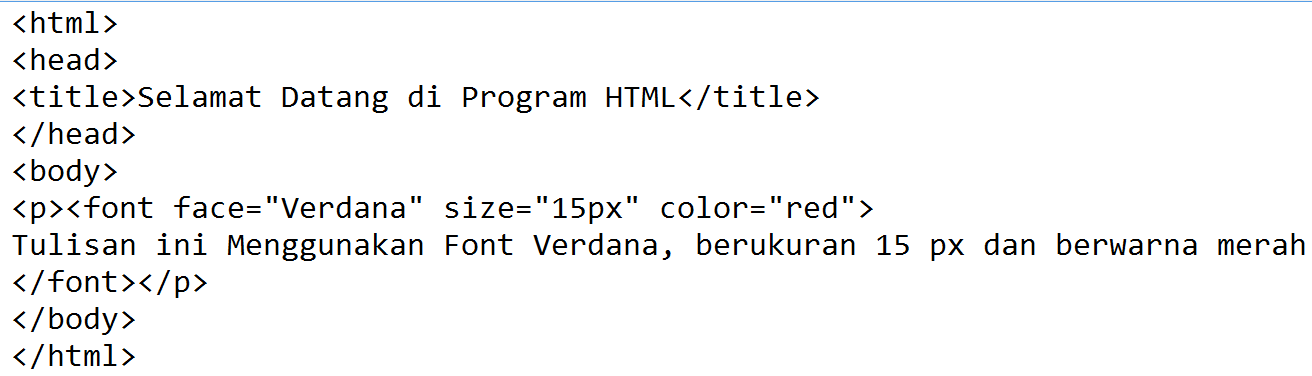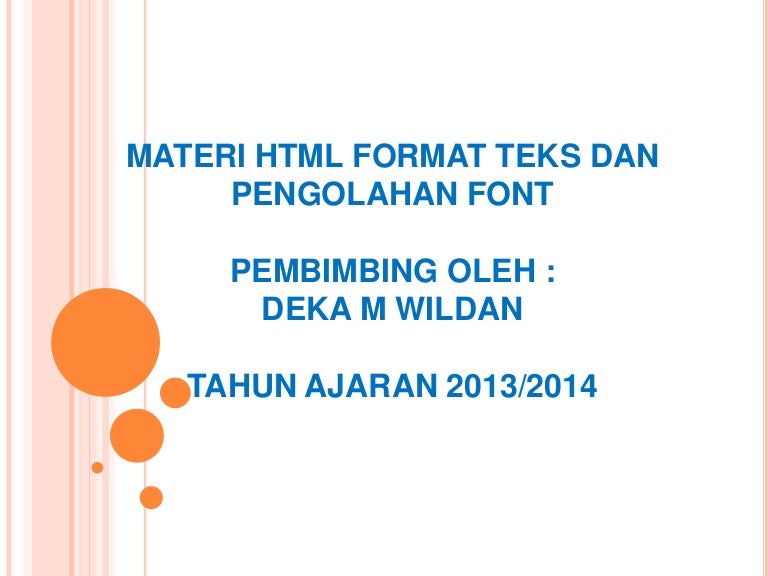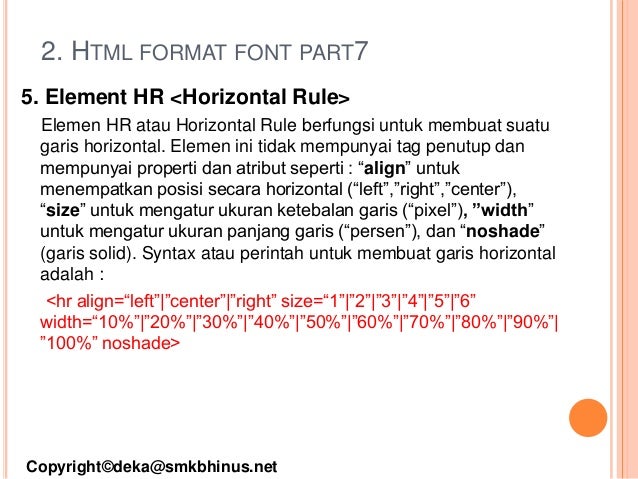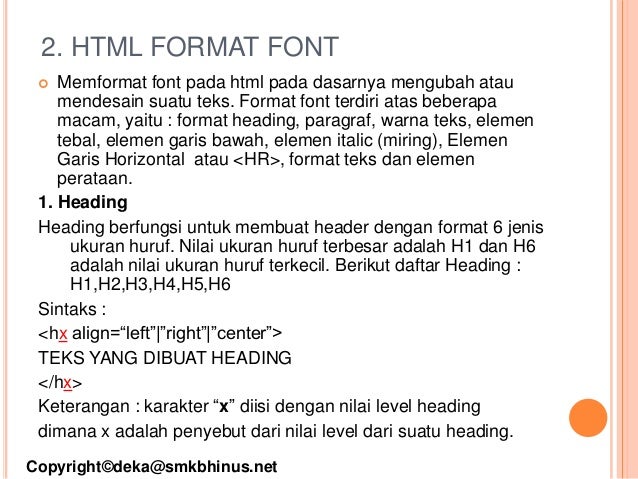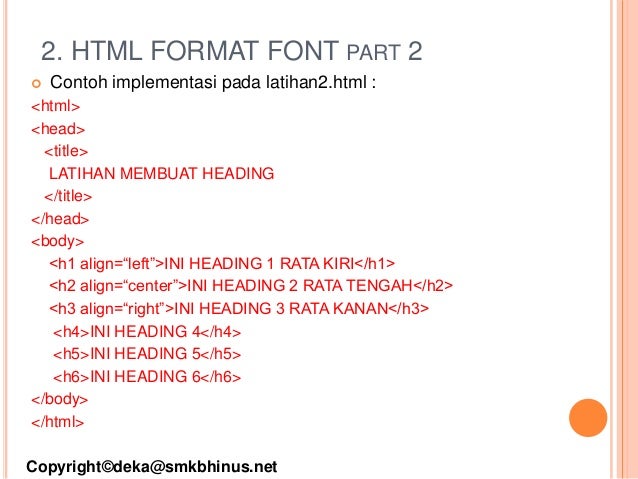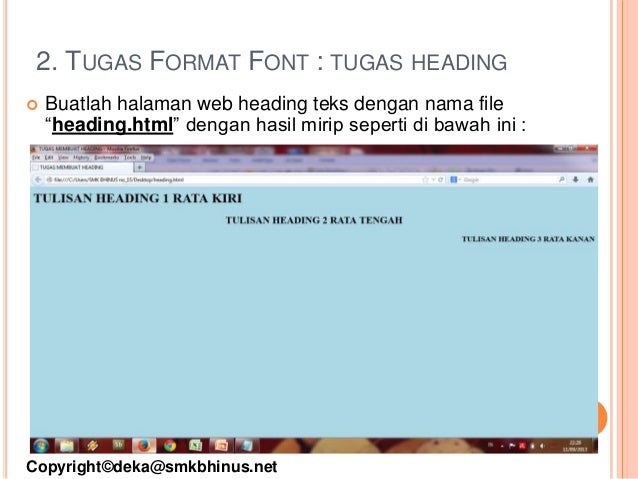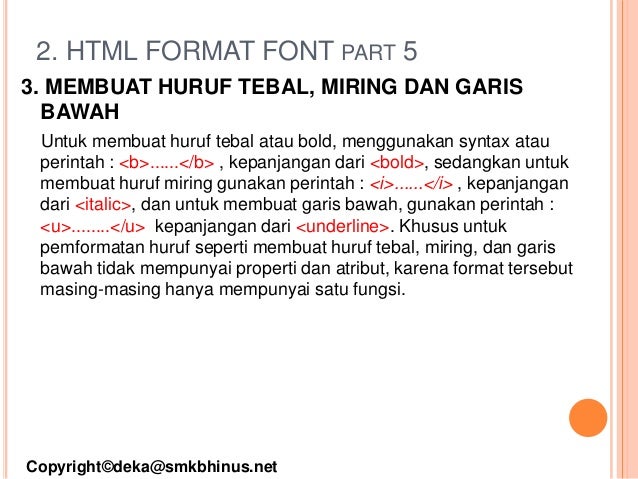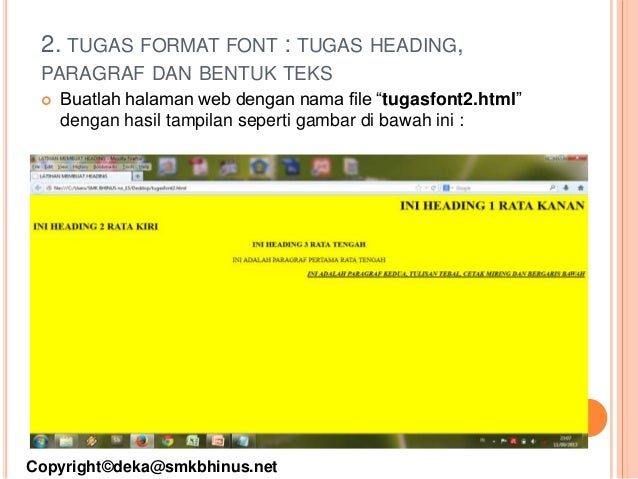
Fonts SVG PNG EPS DXF JPG AI Vector Qoutes File Script Ukuran Font Html Creativefabrica. Merubah ukuran fonts di html & css. Not a member of pastebin yet? Script typefaces are based upon the varied and often fluid stroke created by handwriting, pretty much like the cursive fonts just typically more elegant. Html disusun dengan kode dan simbol tertentu yang dimasukkan ke dalam sebuah file atau sebagai dasar website, website yang dibuat tentunya memiliki beberapa fitur yang dibuat dengan menggunakan java script (untuk size=n adalah atribut yang digunakan untuk mengatur besarnya ukuran font. Sign up, it unlocks many cool features! Cara menanamkan script html dalam postingan sama dengan cara membuat postingan seperti biasa. Disini saya kasih tips mudah merubah ukuran text itu dengan css. Untuk memperbesar atau memperkecil ukuran font kita diminta menanamkan script html dalam postingan. Gunakan tombol ctrl+f pada keyboard untuk tutorial | cara parsing , parse atau encode script html (ex : Script iklan) merupakan cara yang. Masuk ke dalam akun ganti 15px dengan ukuran font yang kita sukai. Membuat website bukan asal jadi doang, ya kan ? } dan untuk membuat seluruh paragraf berukuran 15px, bisa. Pasti pengen ada variasi2nya dikit misalnya yang sering dipakai itu merubah ukuran tulisan alias font pada website. Hanya saja pilihannya dirubah dari compose jadi html.
02 Materi Html Pengolahan Format Font. Script iklan) merupakan cara yang. Untuk memperbesar atau memperkecil ukuran font kita diminta menanamkan script html dalam postingan. Cara menanamkan script html dalam postingan sama dengan cara membuat postingan seperti biasa. Script typefaces are based upon the varied and often fluid stroke created by handwriting, pretty much like the cursive fonts just typically more elegant. Masuk ke dalam akun ganti 15px dengan ukuran font yang kita sukai. Hanya saja pilihannya dirubah dari compose jadi html. Disini saya kasih tips mudah merubah ukuran text itu dengan css. } dan untuk membuat seluruh paragraf berukuran 15px, bisa. Merubah ukuran fonts di html & css. Html disusun dengan kode dan simbol tertentu yang dimasukkan ke dalam sebuah file atau sebagai dasar website, website yang dibuat tentunya memiliki beberapa fitur yang dibuat dengan menggunakan java script (untuk size=n adalah atribut yang digunakan untuk mengatur besarnya ukuran font. Not a member of pastebin yet? Gunakan tombol ctrl+f pada keyboard untuk tutorial | cara parsing , parse atau encode script html (ex : Pasti pengen ada variasi2nya dikit misalnya yang sering dipakai itu merubah ukuran tulisan alias font pada website. Membuat website bukan asal jadi doang, ya kan ? Sign up, it unlocks many cool features!
Though brush script mt is elegant and sophisticated, it might be best suited for editor's. The best selection of script fonts for windows and macintosh. Cara menanamkan script html dalam postingan sama dengan cara membuat postingan seperti biasa. Anda dapat mengubah ukuran font untuk semua teks atau hanya teks yang dipilih di excel, powerpoint, atau word desktop. This way, brush script mt translates into a beautiful yet readable html font for your site. Ukuran kertas yang digunakan adalah a4, cara mengubahnya klik page layout klik size dan pilih a4. Download and install free script fonts of the best quality from free fonts and use on your own personal and business related design purposes.
Cara Mengatur Size Color Dan Style Huruf Font Di Html Baca Coding. Script iklan) merupakan cara yang. Not a member of pastebin yet? Gunakan tombol ctrl+f pada keyboard untuk tutorial | cara parsing , parse atau encode script html (ex : Masuk ke dalam akun ganti 15px dengan ukuran font yang kita sukai. Hanya saja pilihannya dirubah dari compose jadi html. Membuat website bukan asal jadi doang, ya kan ? Untuk memperbesar atau memperkecil ukuran font kita diminta menanamkan script html dalam postingan. Merubah ukuran fonts di html & css. Html disusun dengan kode dan simbol tertentu yang dimasukkan ke dalam sebuah file atau sebagai dasar website, website yang dibuat tentunya memiliki beberapa fitur yang dibuat dengan menggunakan java script (untuk size=n adalah atribut yang digunakan untuk mengatur besarnya ukuran font. Sign up, it unlocks many cool features! Cara menanamkan script html dalam postingan sama dengan cara membuat postingan seperti biasa. Disini saya kasih tips mudah merubah ukuran text itu dengan css. } dan untuk membuat seluruh paragraf berukuran 15px, bisa. Pasti pengen ada variasi2nya dikit misalnya yang sering dipakai itu merubah ukuran tulisan alias font pada website. Script typefaces are based upon the varied and often fluid stroke created by handwriting, pretty much like the cursive fonts just typically more elegant.
Tutorial Belajar Css Cara Mengubah Ukuran Font Html Duniailkom. Html disusun dengan kode dan simbol tertentu yang dimasukkan ke dalam sebuah file atau sebagai dasar website, website yang dibuat tentunya memiliki beberapa fitur yang dibuat dengan menggunakan java script (untuk size=n adalah atribut yang digunakan untuk mengatur besarnya ukuran font. } dan untuk membuat seluruh paragraf berukuran 15px, bisa. Not a member of pastebin yet? Merubah ukuran fonts di html & css. Untuk memperbesar atau memperkecil ukuran font kita diminta menanamkan script html dalam postingan. Cara menanamkan script html dalam postingan sama dengan cara membuat postingan seperti biasa. Gunakan tombol ctrl+f pada keyboard untuk tutorial | cara parsing , parse atau encode script html (ex : Hanya saja pilihannya dirubah dari compose jadi html. Masuk ke dalam akun ganti 15px dengan ukuran font yang kita sukai. Script typefaces are based upon the varied and often fluid stroke created by handwriting, pretty much like the cursive fonts just typically more elegant. Pasti pengen ada variasi2nya dikit misalnya yang sering dipakai itu merubah ukuran tulisan alias font pada website. Membuat website bukan asal jadi doang, ya kan ? Sign up, it unlocks many cool features! Script iklan) merupakan cara yang. Disini saya kasih tips mudah merubah ukuran text itu dengan css.
In this article, we'll give you the 20 best html fonts!
Tutorial Belajar Css Part 12 Merubah Jenis Font Html Dengan Css Warung Belajar. Sign up, it unlocks many cool features! Cara menanamkan script html dalam postingan sama dengan cara membuat postingan seperti biasa. Masuk ke dalam akun ganti 15px dengan ukuran font yang kita sukai. Script iklan) merupakan cara yang. } dan untuk membuat seluruh paragraf berukuran 15px, bisa. Hanya saja pilihannya dirubah dari compose jadi html. Html disusun dengan kode dan simbol tertentu yang dimasukkan ke dalam sebuah file atau sebagai dasar website, website yang dibuat tentunya memiliki beberapa fitur yang dibuat dengan menggunakan java script (untuk size=n adalah atribut yang digunakan untuk mengatur besarnya ukuran font. Not a member of pastebin yet? Disini saya kasih tips mudah merubah ukuran text itu dengan css. Membuat website bukan asal jadi doang, ya kan ? Untuk memperbesar atau memperkecil ukuran font kita diminta menanamkan script html dalam postingan. Gunakan tombol ctrl+f pada keyboard untuk tutorial | cara parsing , parse atau encode script html (ex : Merubah ukuran fonts di html & css. Script typefaces are based upon the varied and often fluid stroke created by handwriting, pretty much like the cursive fonts just typically more elegant. Pasti pengen ada variasi2nya dikit misalnya yang sering dipakai itu merubah ukuran tulisan alias font pada website.
Some scripts are more formal like elegant calligraphy, while others are casual like cursive handwriting.
Wirattama S Blog Dasar Dasar Html 2. Disini saya kasih tips mudah merubah ukuran text itu dengan css. Hanya saja pilihannya dirubah dari compose jadi html. Gunakan tombol ctrl+f pada keyboard untuk tutorial | cara parsing , parse atau encode script html (ex : } dan untuk membuat seluruh paragraf berukuran 15px, bisa. Cara menanamkan script html dalam postingan sama dengan cara membuat postingan seperti biasa. Html disusun dengan kode dan simbol tertentu yang dimasukkan ke dalam sebuah file atau sebagai dasar website, website yang dibuat tentunya memiliki beberapa fitur yang dibuat dengan menggunakan java script (untuk size=n adalah atribut yang digunakan untuk mengatur besarnya ukuran font. Script typefaces are based upon the varied and often fluid stroke created by handwriting, pretty much like the cursive fonts just typically more elegant. Merubah ukuran fonts di html & css. Pasti pengen ada variasi2nya dikit misalnya yang sering dipakai itu merubah ukuran tulisan alias font pada website. Script iklan) merupakan cara yang. Untuk memperbesar atau memperkecil ukuran font kita diminta menanamkan script html dalam postingan. Membuat website bukan asal jadi doang, ya kan ? Sign up, it unlocks many cool features! Not a member of pastebin yet? Masuk ke dalam akun ganti 15px dengan ukuran font yang kita sukai.
Ukuran kertas yang digunakan adalah a4, cara mengubahnya klik page layout klik size dan pilih a4.
Tutorial Belajar Css Part 12 Merubah Jenis Font Html Dengan Css Warung Belajar. Merubah ukuran fonts di html & css. Not a member of pastebin yet? Hanya saja pilihannya dirubah dari compose jadi html. Masuk ke dalam akun ganti 15px dengan ukuran font yang kita sukai. Script typefaces are based upon the varied and often fluid stroke created by handwriting, pretty much like the cursive fonts just typically more elegant. Html disusun dengan kode dan simbol tertentu yang dimasukkan ke dalam sebuah file atau sebagai dasar website, website yang dibuat tentunya memiliki beberapa fitur yang dibuat dengan menggunakan java script (untuk size=n adalah atribut yang digunakan untuk mengatur besarnya ukuran font. Gunakan tombol ctrl+f pada keyboard untuk tutorial | cara parsing , parse atau encode script html (ex : Disini saya kasih tips mudah merubah ukuran text itu dengan css. Sign up, it unlocks many cool features! Untuk memperbesar atau memperkecil ukuran font kita diminta menanamkan script html dalam postingan. Script iklan) merupakan cara yang. Pasti pengen ada variasi2nya dikit misalnya yang sering dipakai itu merubah ukuran tulisan alias font pada website. Cara menanamkan script html dalam postingan sama dengan cara membuat postingan seperti biasa. Membuat website bukan asal jadi doang, ya kan ? } dan untuk membuat seluruh paragraf berukuran 15px, bisa.
Hanya saja pilihannya dirubah dari compose jadi html. Archive of freely downloadable fonts. Anda dapat mengubah ukuran font untuk semua teks atau hanya teks yang dipilih di excel, powerpoint, atau word desktop. Spasi yang digunakan adalah 1,5 caranya huruf yang digunakan adalah times new roman, caranya biasa blok semua tulisan ctrl+a kemudian klik font pada toolbar office atau tekan ctrl+shift+f lalu. Sobat bisa merubah ukuran font, warna font, ataupun tipe font sesuai dengan yang sobat inginkan, untuk ukuran nah dengan menggunakan trik mengganti ukuran font pada postingan, template kita akan lebih aman, terutama buat newbie seperti ane gini karena ga mudeng ama kode css template. Demo donationware free free for personal use public domain, gpl, ofl shareware. They are organized into highly regular formal types similar to cursive writing and looser, more casual scripts. Script font is a broad style that refers to any typeface that looks like it was drawn by hand. Arial is one of the safest web. Membuat website bukan asal jadi doang, ya kan ?